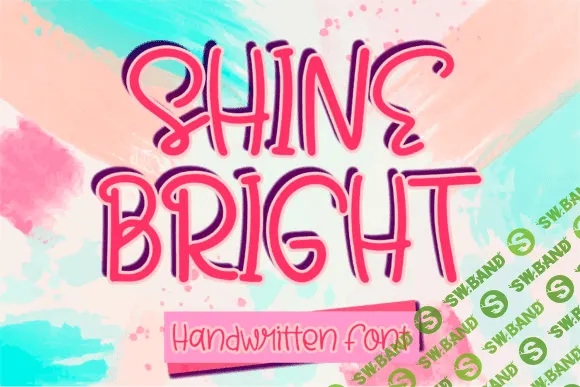
Название: Shine Bright Font
Shine Bright - это простой и изящный рукописный шрифт.
Он может быть использован для различных целей, таких как логотипы, свадебные приглашения, заголовки, футболки, фирменные бланки, вывески, этикетки, новости, плакаты, значки и многое другое.